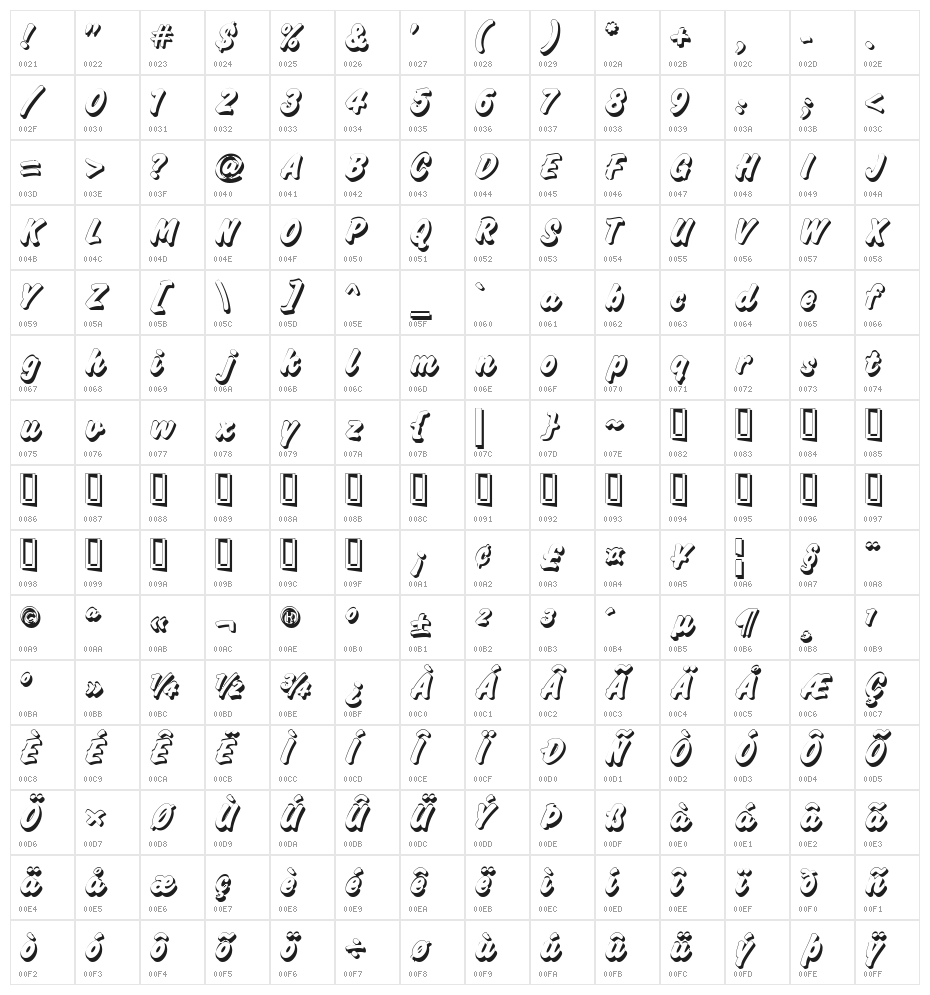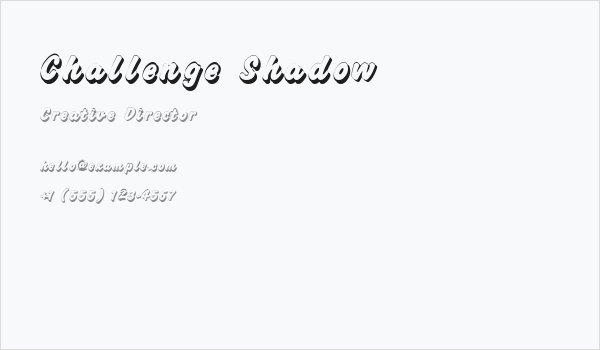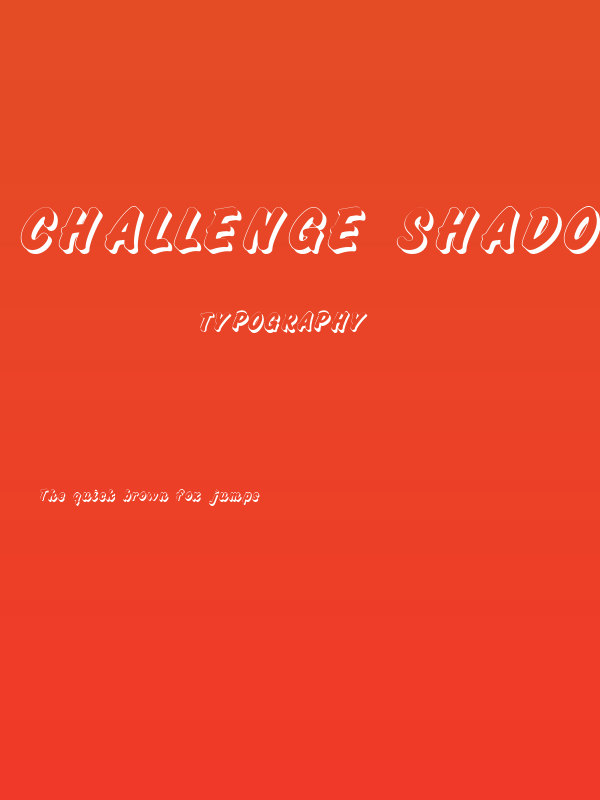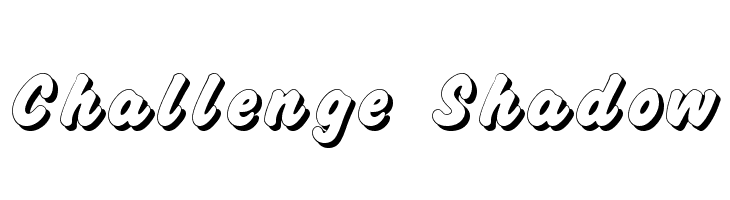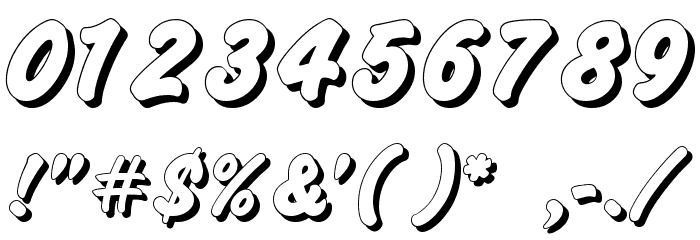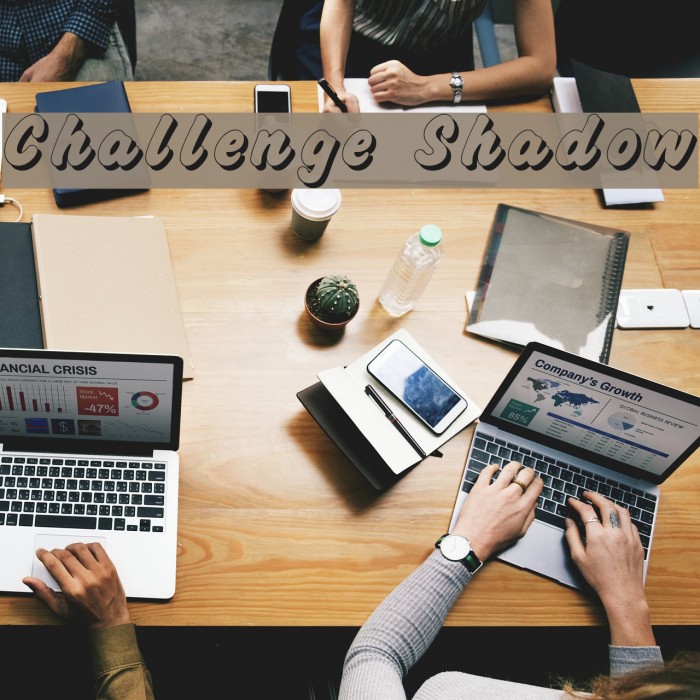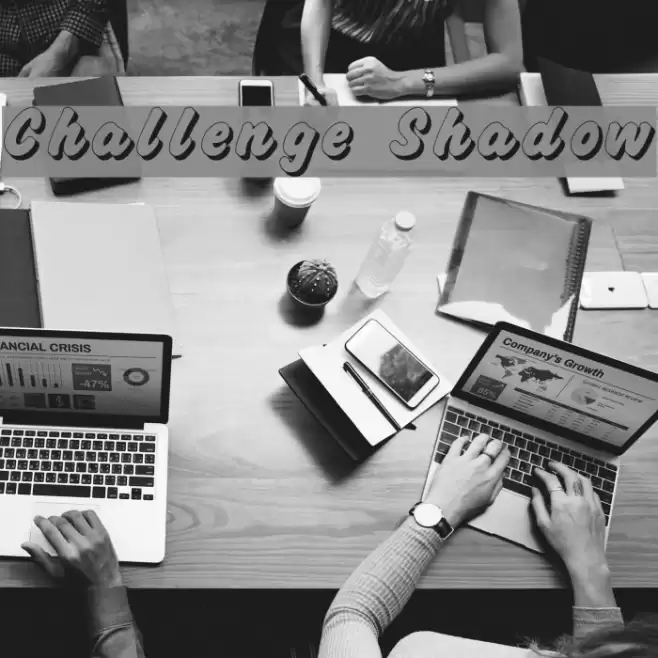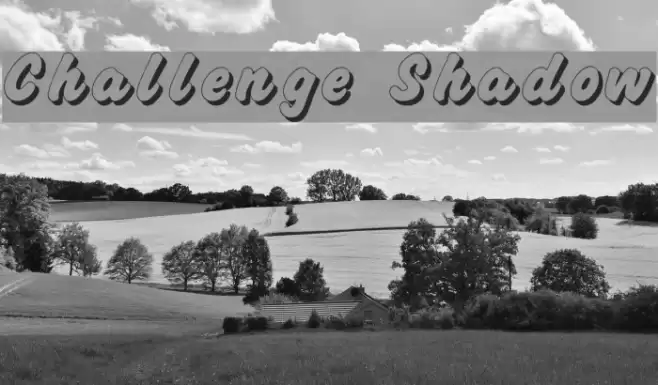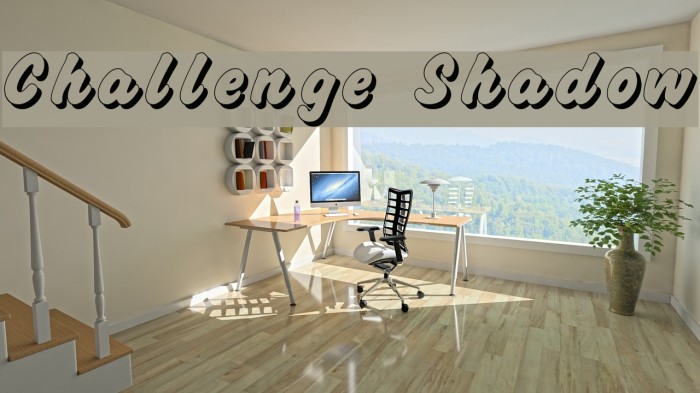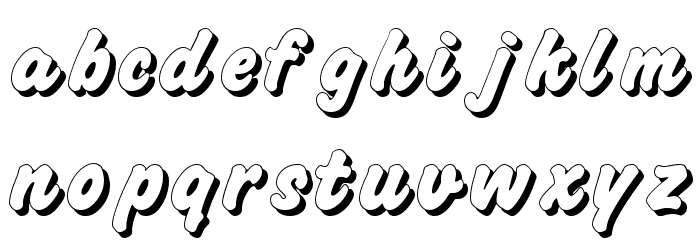
Challenge Shadow Font
| Stile generale | Playful, Energetic, Decorative |
| Progetti proposti | Ideal for posters, children's books, comic titles, and playful branding projects. |